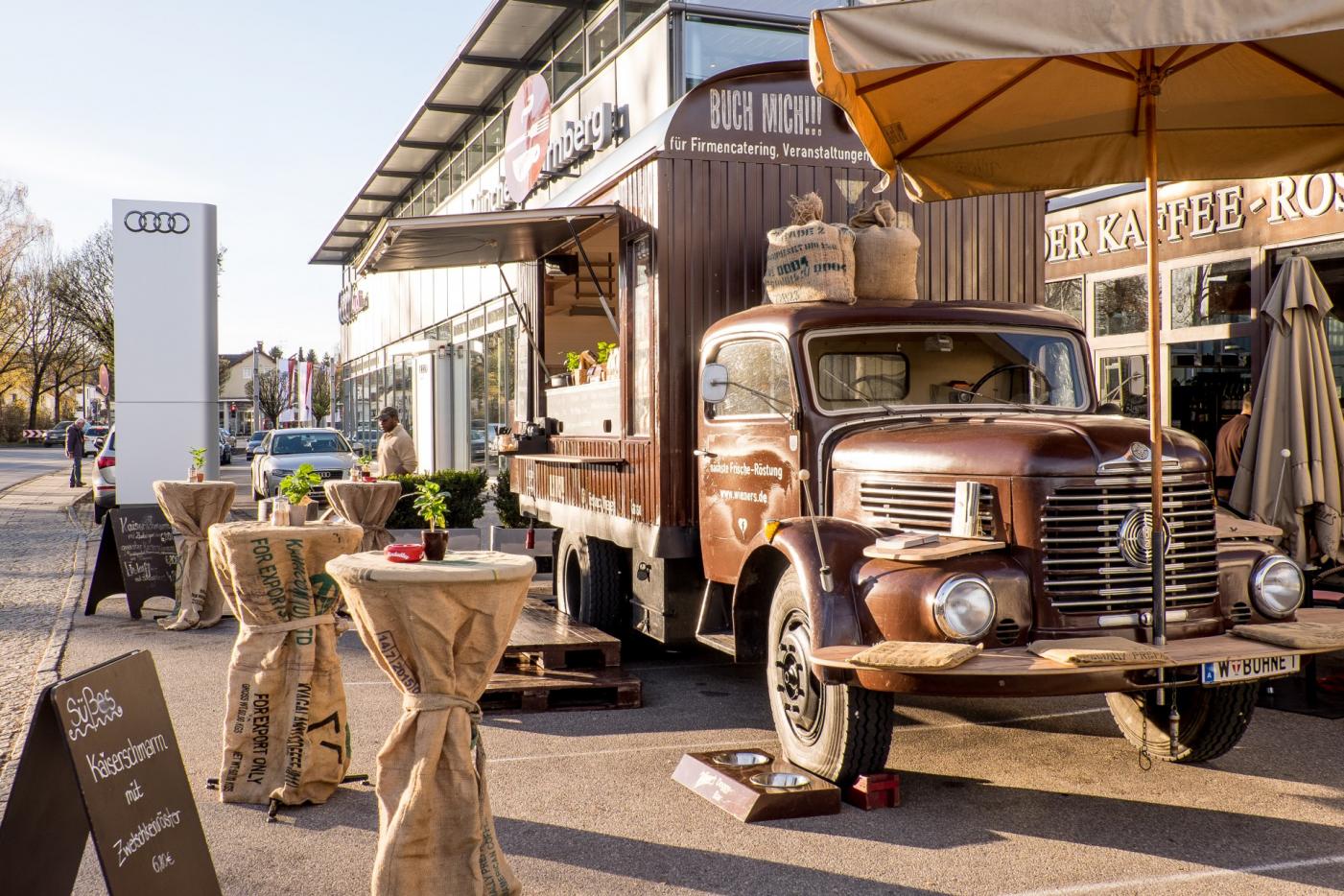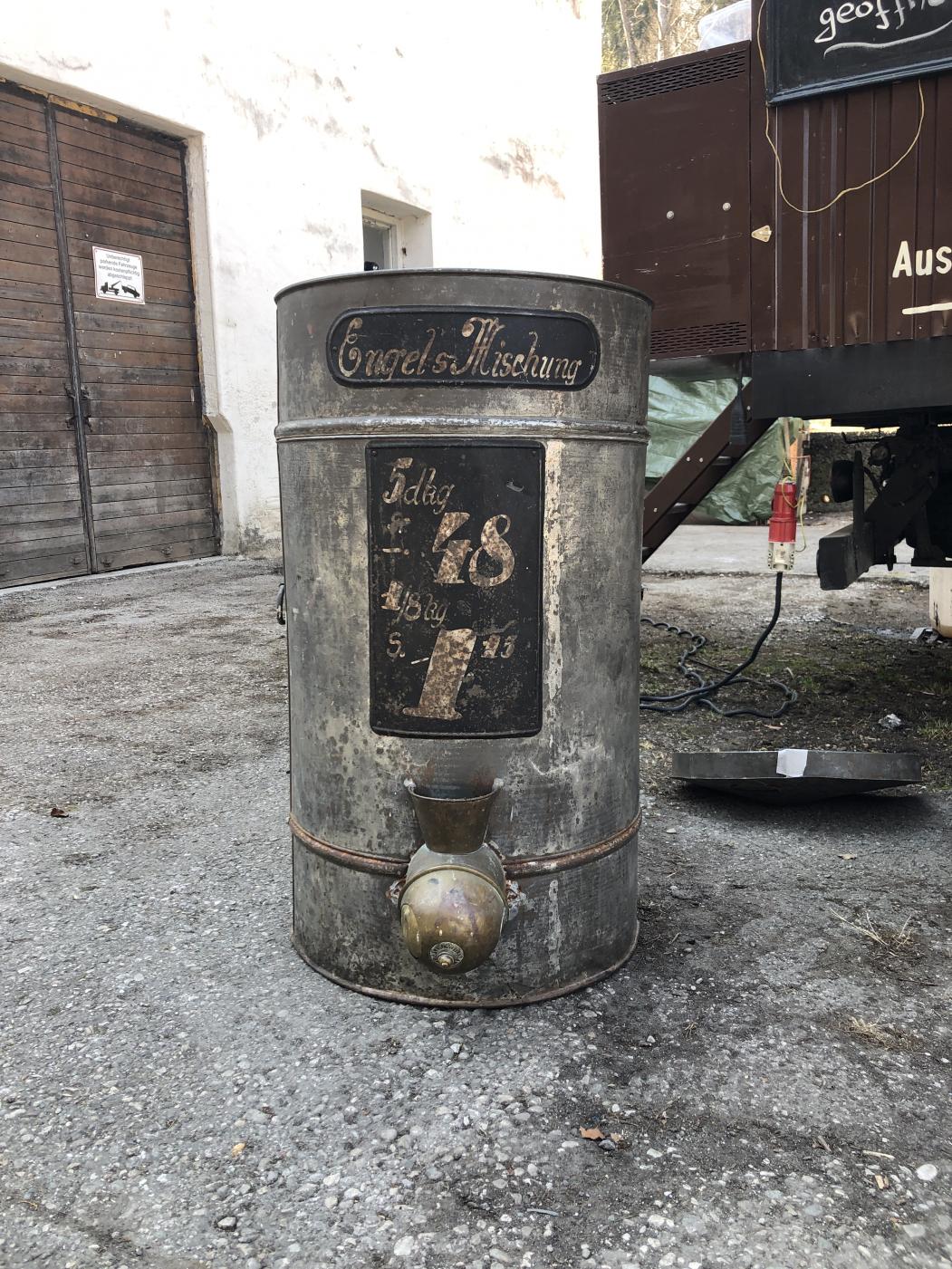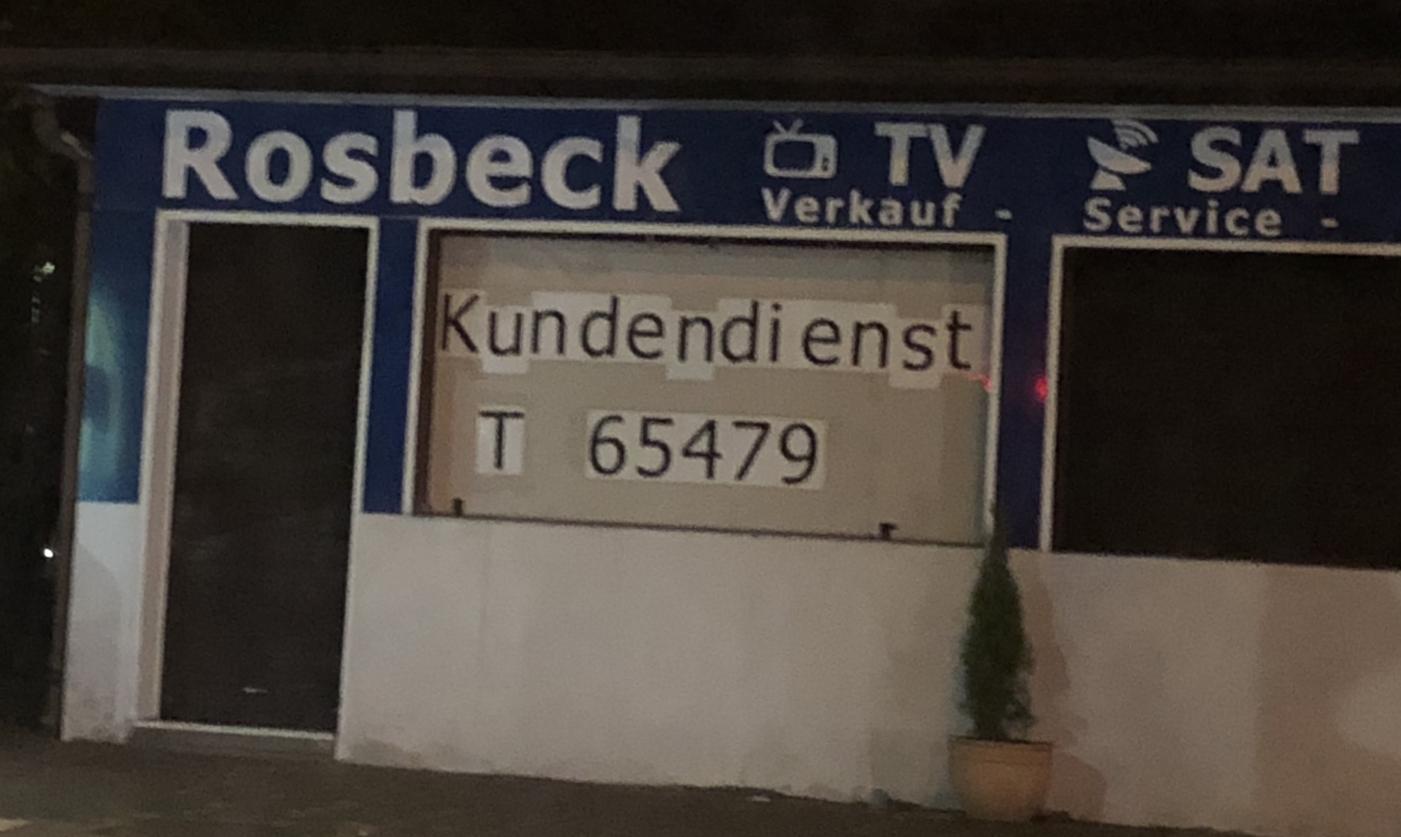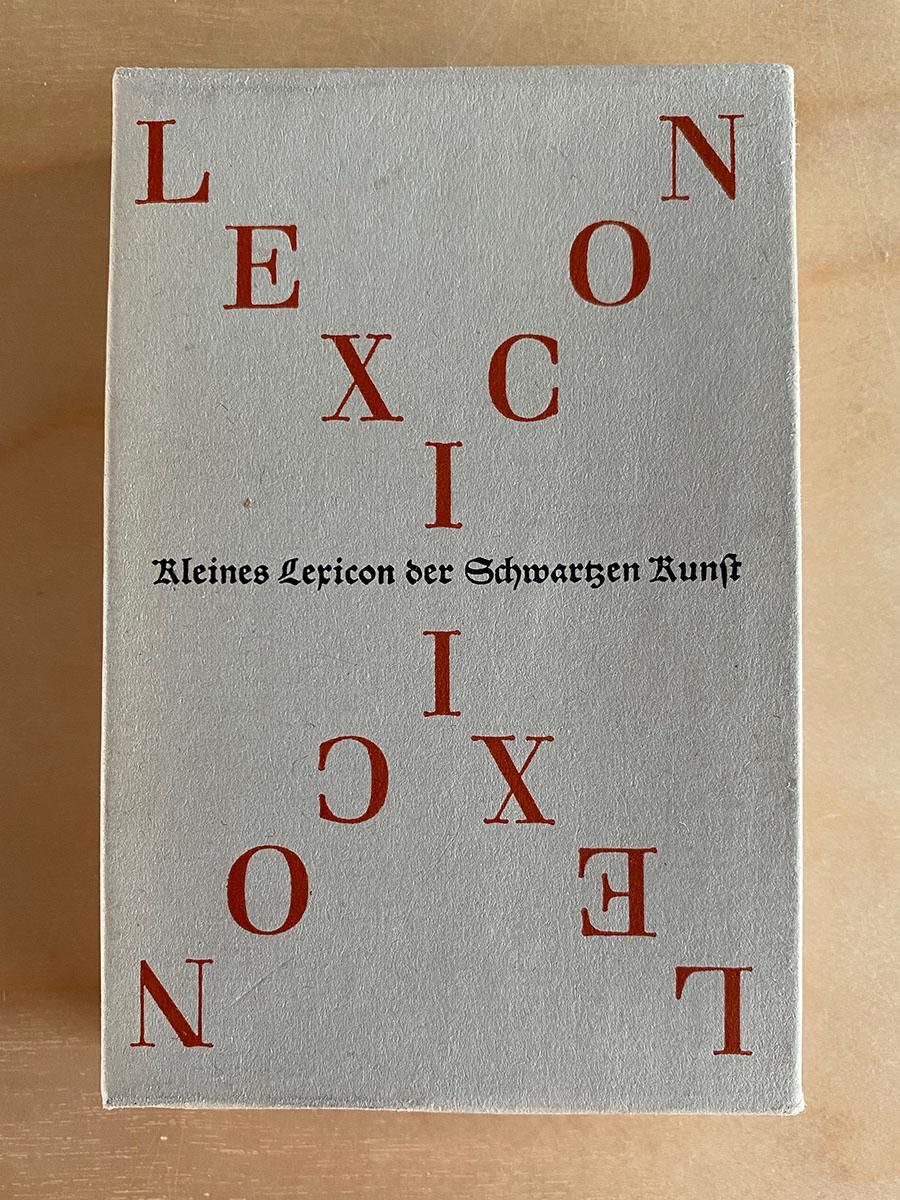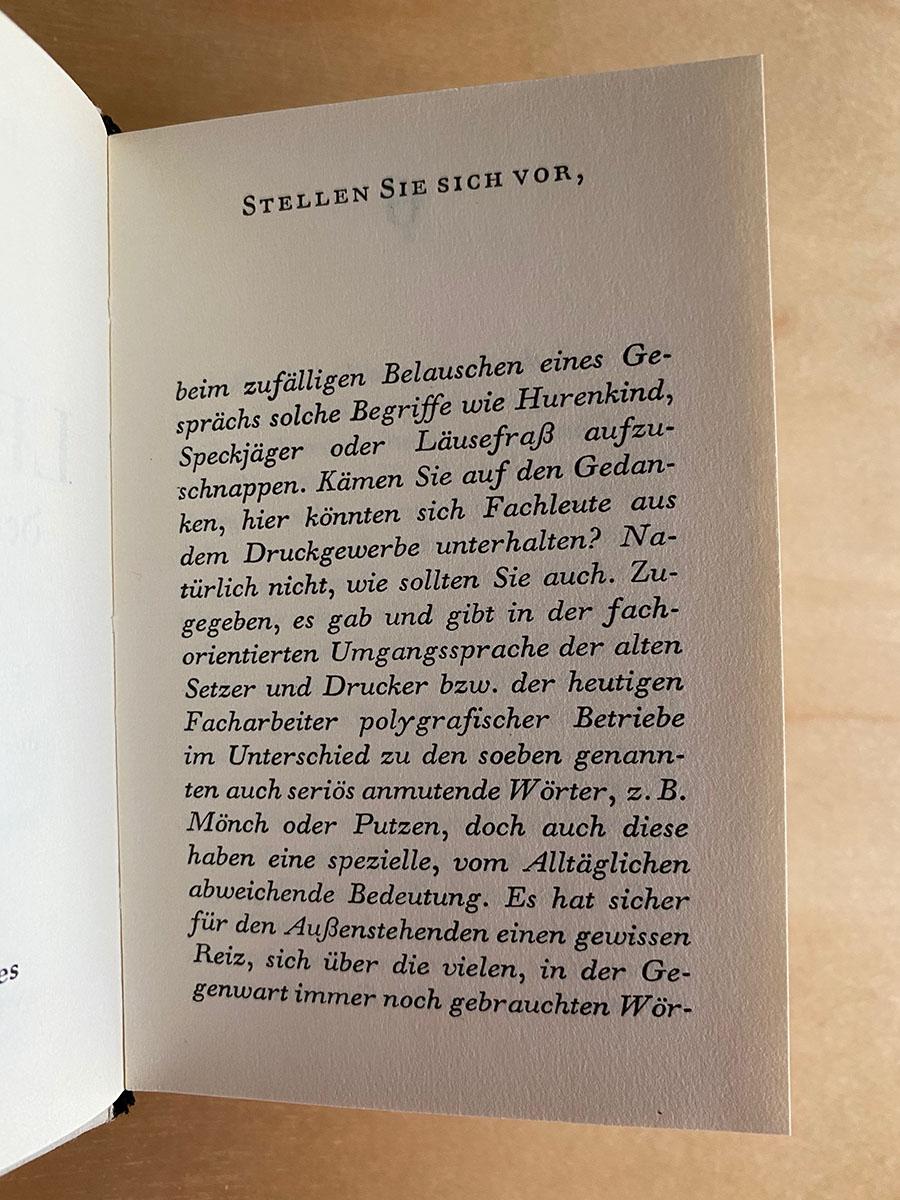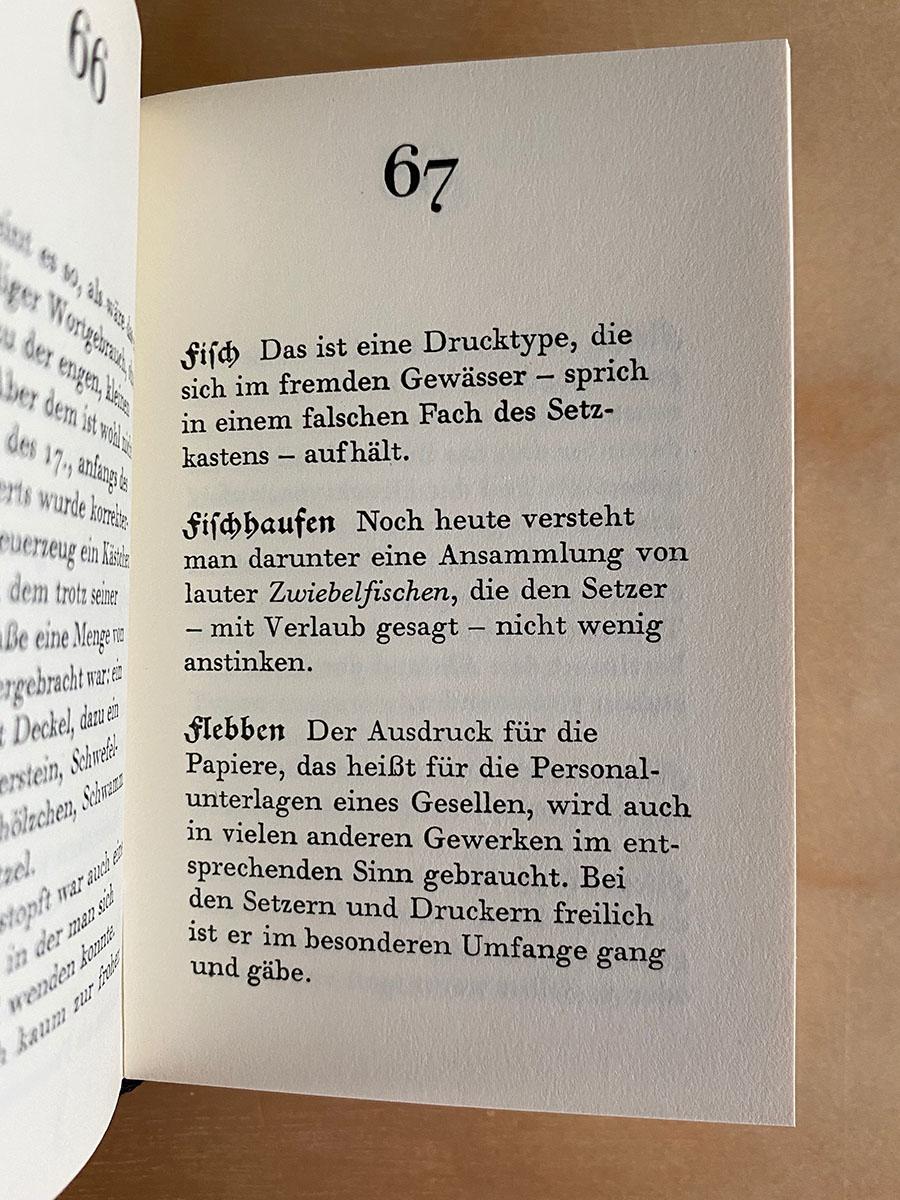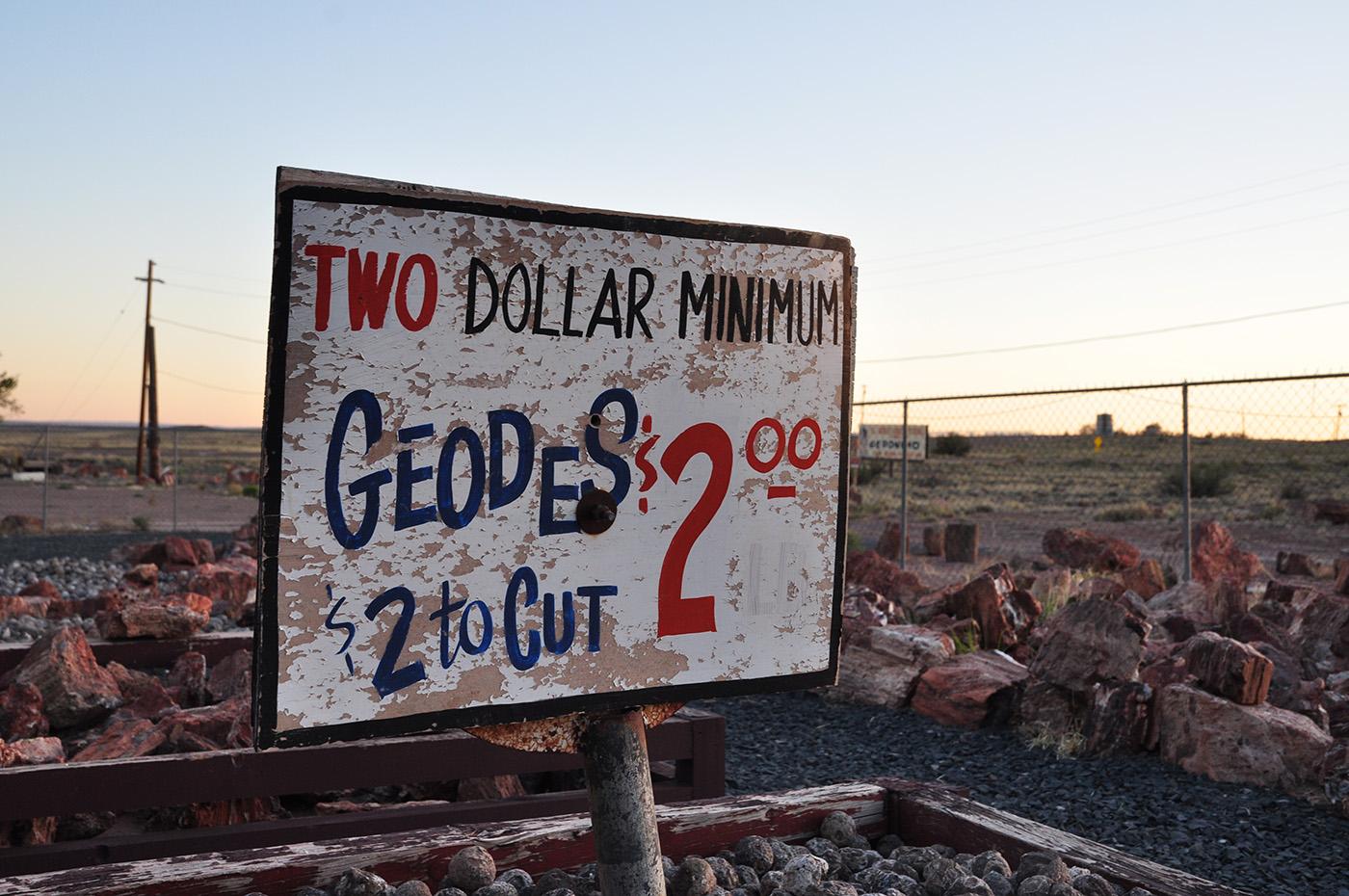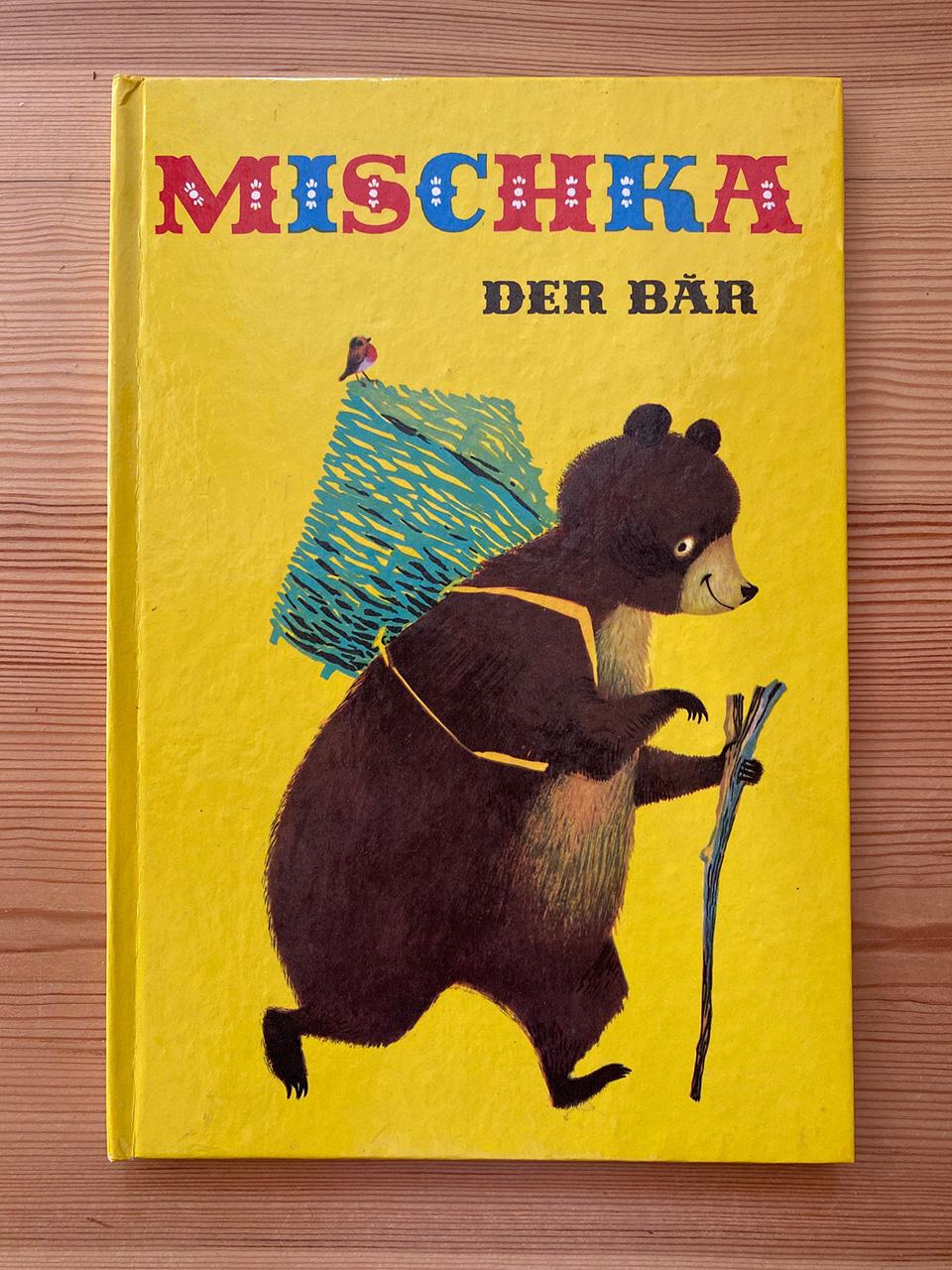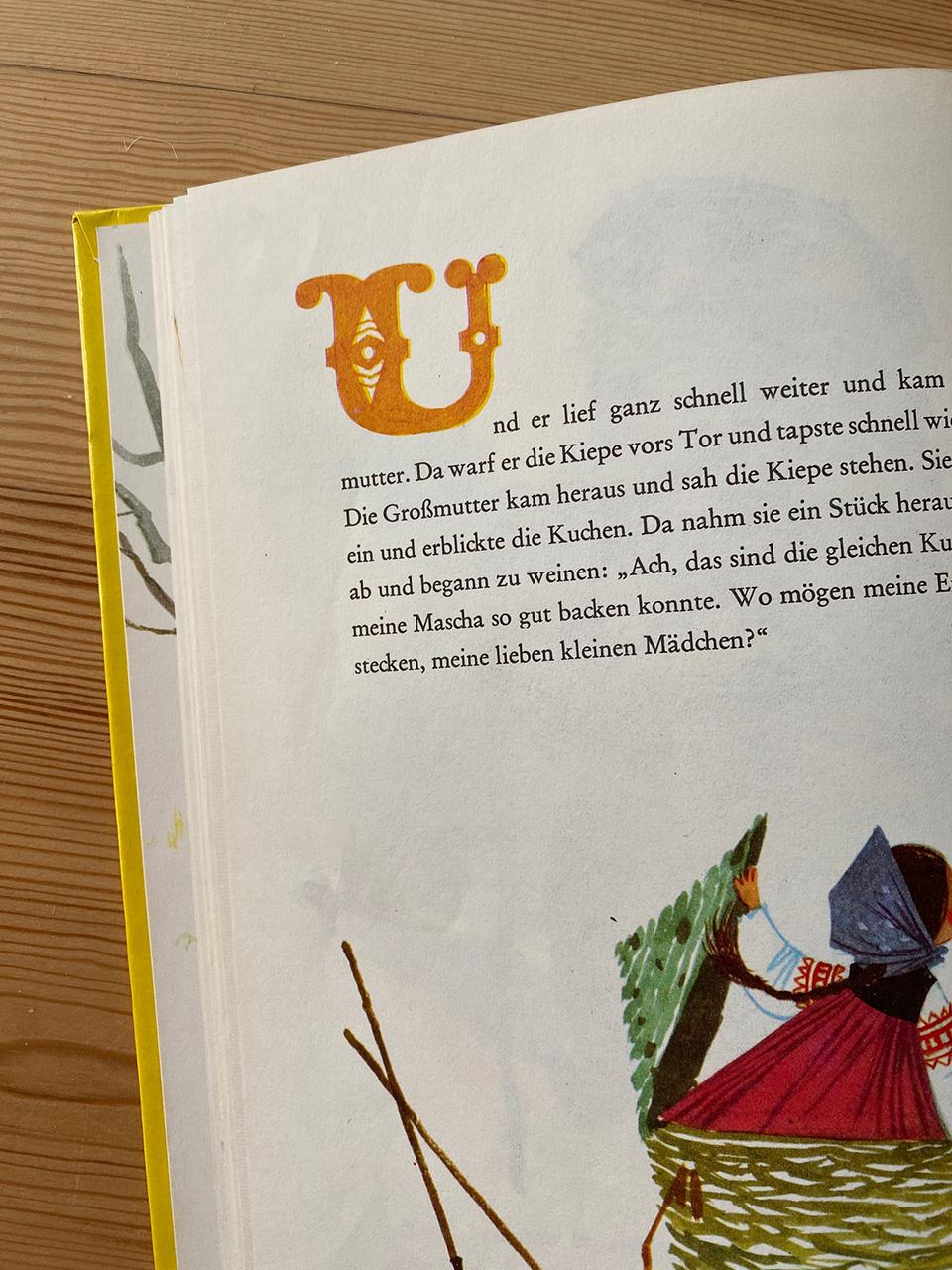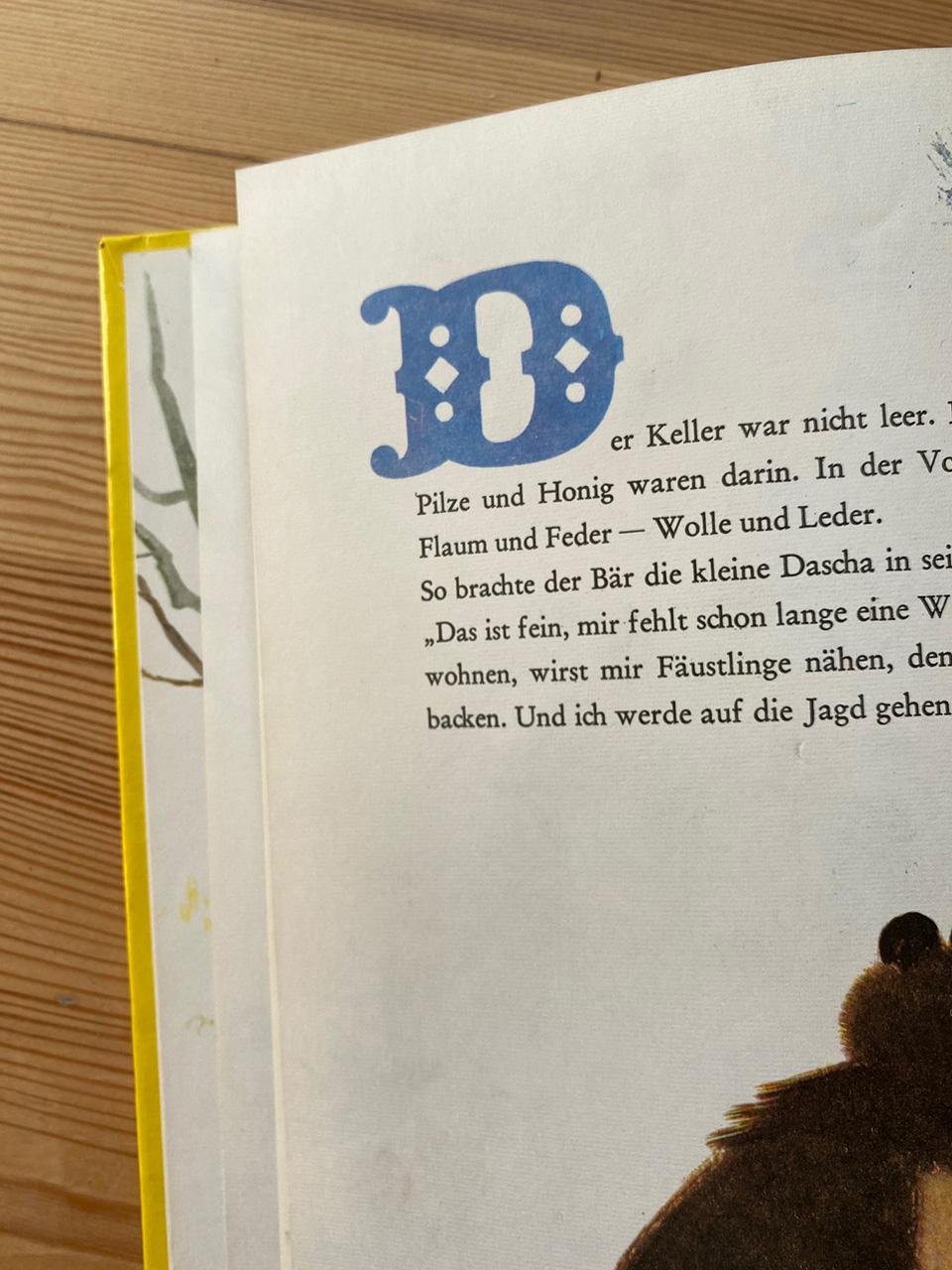
Also wenn schon Trickfilm-Musik, dann bin ich eindeutig hierfür:
Ja, die Musik war toll! Die Serie habe ich dennoch nicht gemocht. Bei Musik fällt mir vor allem das fetzige Intro von Wickie ein. Sindbad hat auch ein tolles Intro.
»Der Băr«? Das tolle Buch ist dann wohl in Siebenbürgen entstanden und der Setzer hatte nur einen ihm von der Zentralregierung zugeteilten rumänischen Zeichensatz zur Hand. 🤔
Die Mülltonne meines Lieblings-Kaffetrucks (Steyr Truck Bj 1962):
Was sind das für papierne Etwasse? :aschehaupt:
Einkaufstüten aus dem DDR-Kaufmannsladen-Bedarf ... ungefähr EC-Kartengröße.
Ich weiß nicht, ob es Nostalgie ist, aber ich finde die Farben und die (durch die begrenzten Möglichkeiten gesetzte) Gestaltung jener Zeit schön, Ost wie West.
Ich habe hier noch ein schönes Rätsel für euch: Welche Buchstaben stehen auf dem Kopf? Begründe deinen Lösungsweg …
Manche Lehrer scheinen die Schule sehr zu vermissen :hammer:
Habe ich eben im Bücheregal meiner Eltern entdeckt und mich sehr gefreut. Gab es auch in Leder gebunden – ich schätze aber nur über Beziehungen.
Eine hoffentlich nicht zu dumme Frage eines unbedarften Wessies: ich stelle mir unter einer Offizin einen Privatbetrieb vor. Ist das der Fall? Und wenn ja, wurden die Publikationen vom Staat kontrolliert oder zensiert?
Read me! Publikationen wurden natürlich kontrolliert. Bei dem Thema des Büchleins wird es da aber keine Probleme gegeben haben ...
Hier und hier gibt es noch einige Infos zu Gert Wunderlich, der das Büchlein gestaltet hat. Er hat auch etliche Schriften für Typoart entworfen ...
Alle Personen und Organisationen in der DDR unterlagen sowohl expliziter als auch Selbstzensur. Das ist das Wesen einer totalitären Diktatur. Mit der Organisationsform hatte das nur sehr wenig zu tun. Auch wenn Offizin Andersen Nexö kein VEB gewesen sein sollte, hätte der Betrieb natürlich nicht drucken dürfen, was er wollte. In mancherlei Hinsicht hatten die wenigen verbliebenen privaten Akteure sogar noch weniger Freiräume als Angehörige staatliche Organisationen, auch und gerade im Kulturbereich im weitesten Sinn.